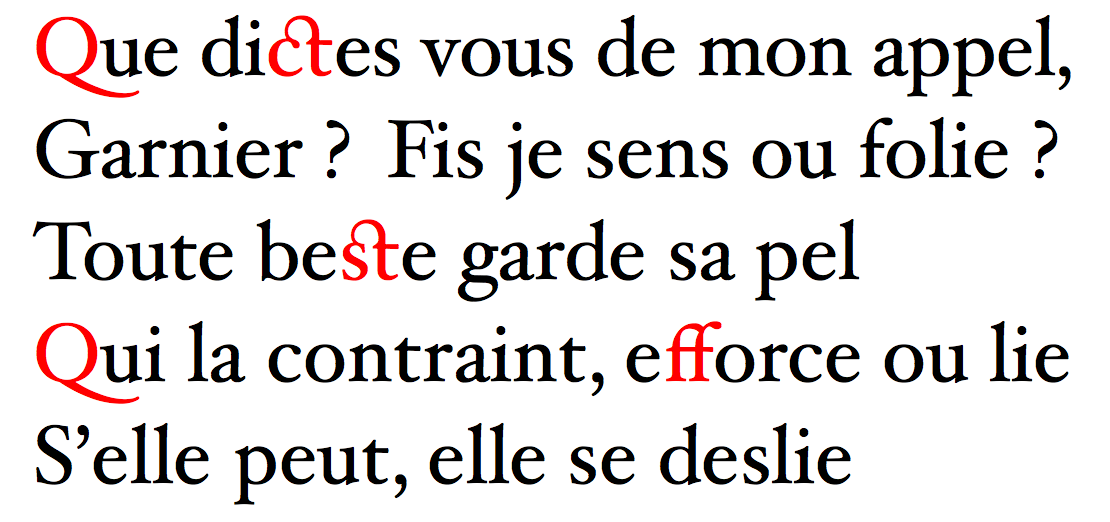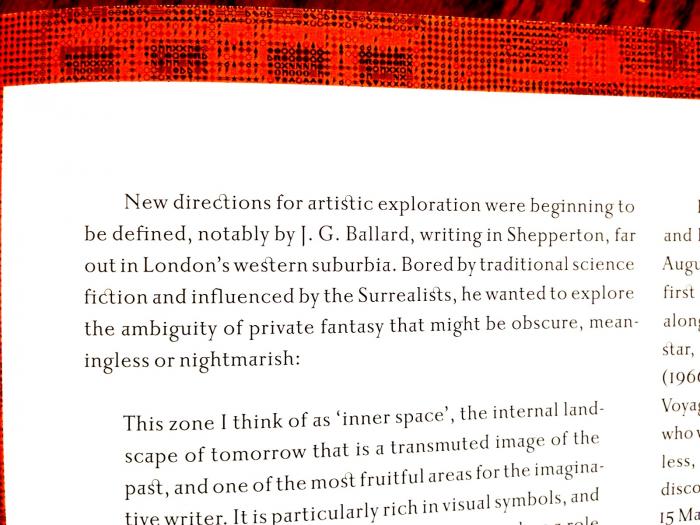
Seltsame Schrift im Ausstellungs-Katalog "David Bowie is"
Hallo, ich habe mir den Katalog gekauft "David Bowie is" und bin verwundert über die Schrift. Zwischen allen s und t ist ein Verbindungsbogen, ebenso zwischen c und t.
Weiß jemand, was es damit auf sich hat?
Es lässt sich jedenfalls sehr schwer lesen, die Bogen lenken sehr ab.
Ich lade einen Ausschnitt einer Seite hoch und bin gespannt auf Antworten.post-34649-0-63406300-1461140114_thumb.j
Ergänzend zur Antwort von Bertel: Es handelt sich hierbei um sogen. Ligaturen, also verbundene Buchstaben. Die Zusammenstellungen von ct und st werden im Englischen auch als discretionary ligatures, also wahlfreie oder Ermessens-Ligaturen bezeichnet, ein anderes und sehr sinnvolles Beispiel für Ligaturen ist in vielen Schriften das fi, falls bei einer Aneinderreihung der beiden Einzelbuchstaben der Bogen des f und der Punkt des i in unschöner Weise aneinanderstießen.
Das richtige OpenType-Feature wäre hiezu „Bedingte Ligaturen“ (discretionary ligatures). Also Schmuckligaturen, die eher bei größeren Schriftgraden verwendet werden.
Ligaturen, wie fi etc. sind „Standardligaturen“, also nicht mit den Schmuckligaturen zu verwechseln.
Mittlerweile wurden drei unterschiedliche OpenType-Features angesprochen:
a) „Swash“ sind die Schwungbuchstaben.
b) Bedingte Ligaturen (wie im Beispiel)
c) Standardligaturen
Vielleicht noch eine Veranschaulichung:
The_beauty_of_latex_ligatures.png
Ich war da etwas daneben gelegen, BerndH und Erwin Krump haben das dankenswerterweise präzisiert – es sind nicht die von mir genannten Swashes, sondern die bedingten Ligaturen. Aber auch die lassen sich ein- und ausschalten.